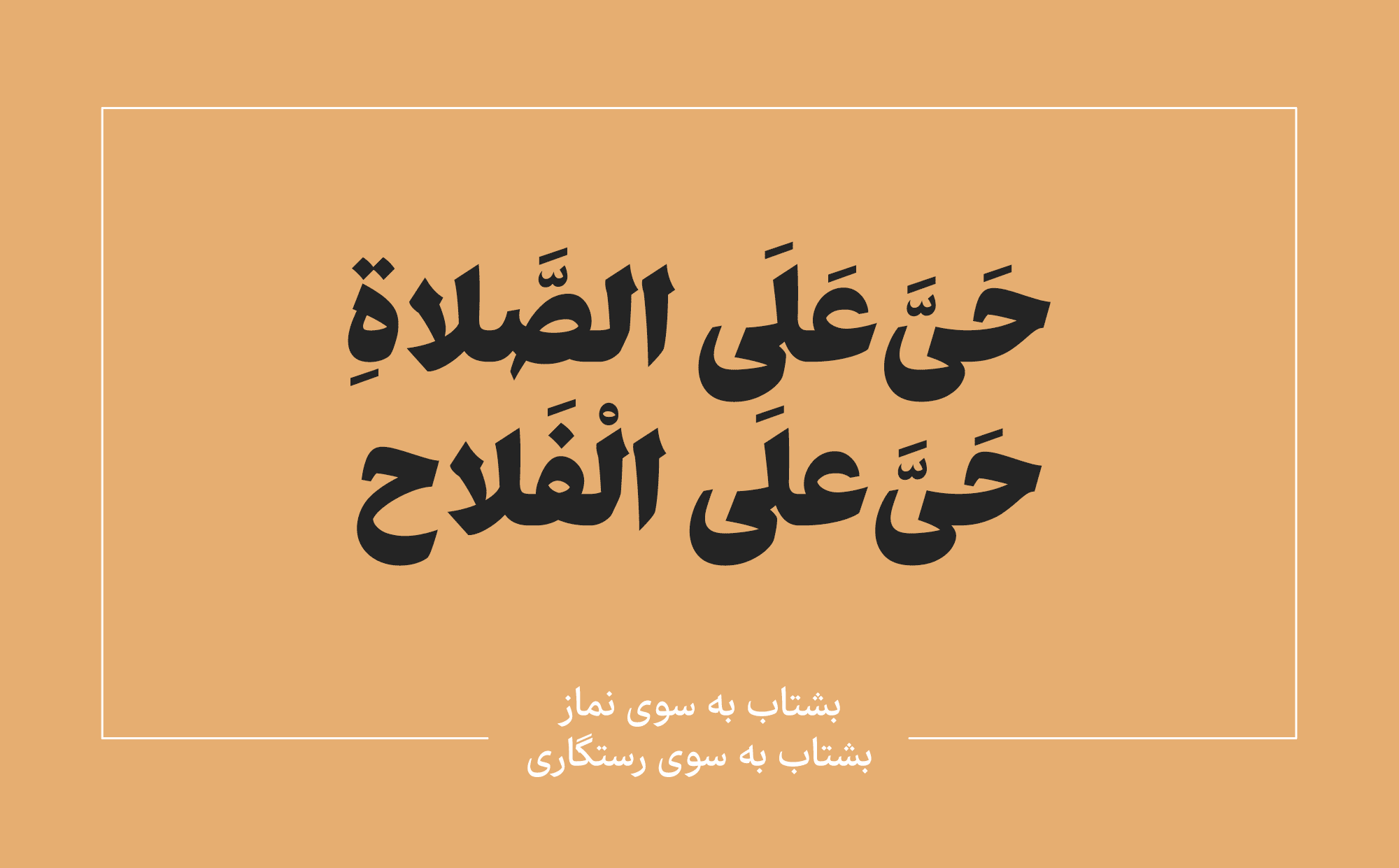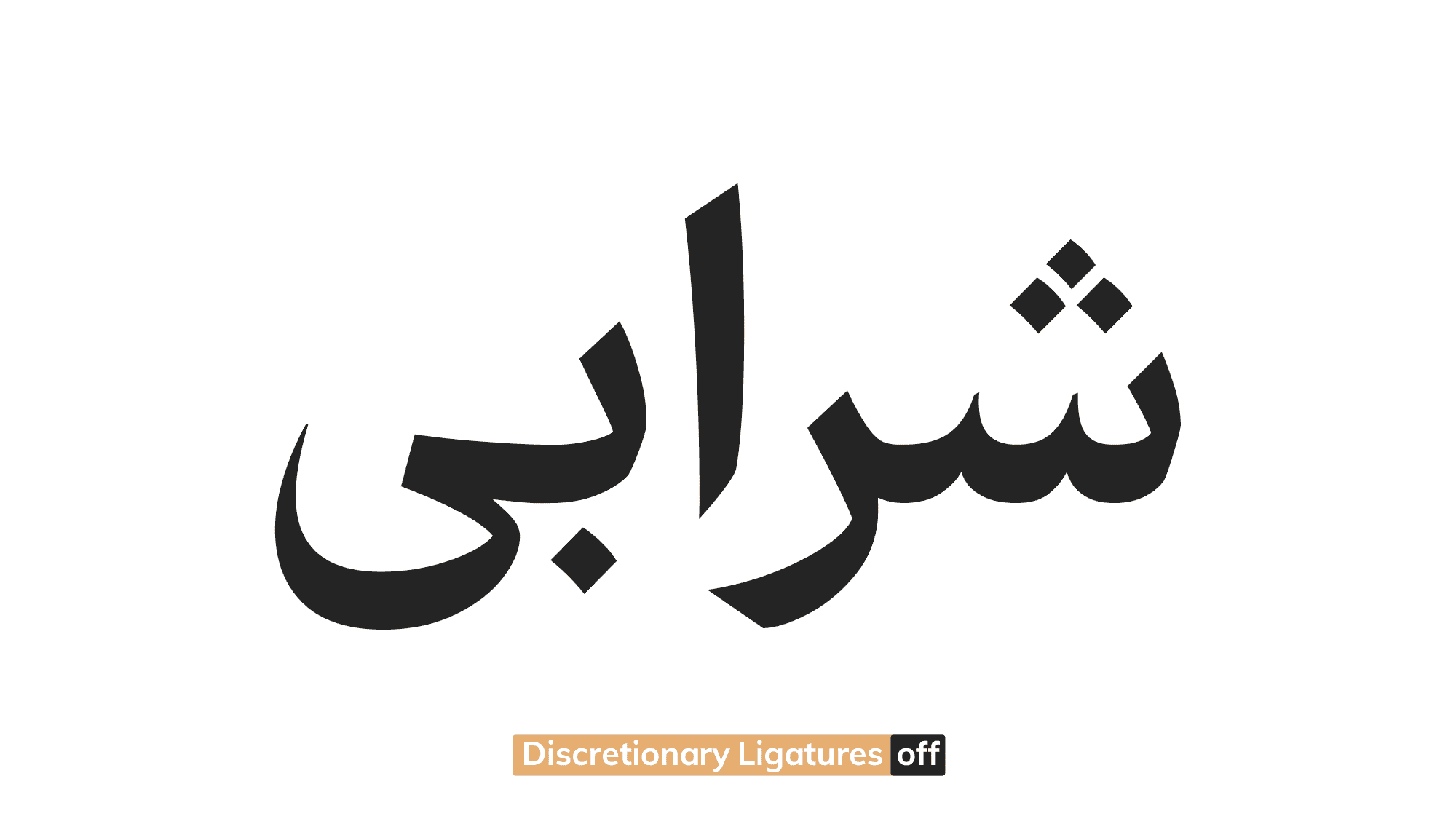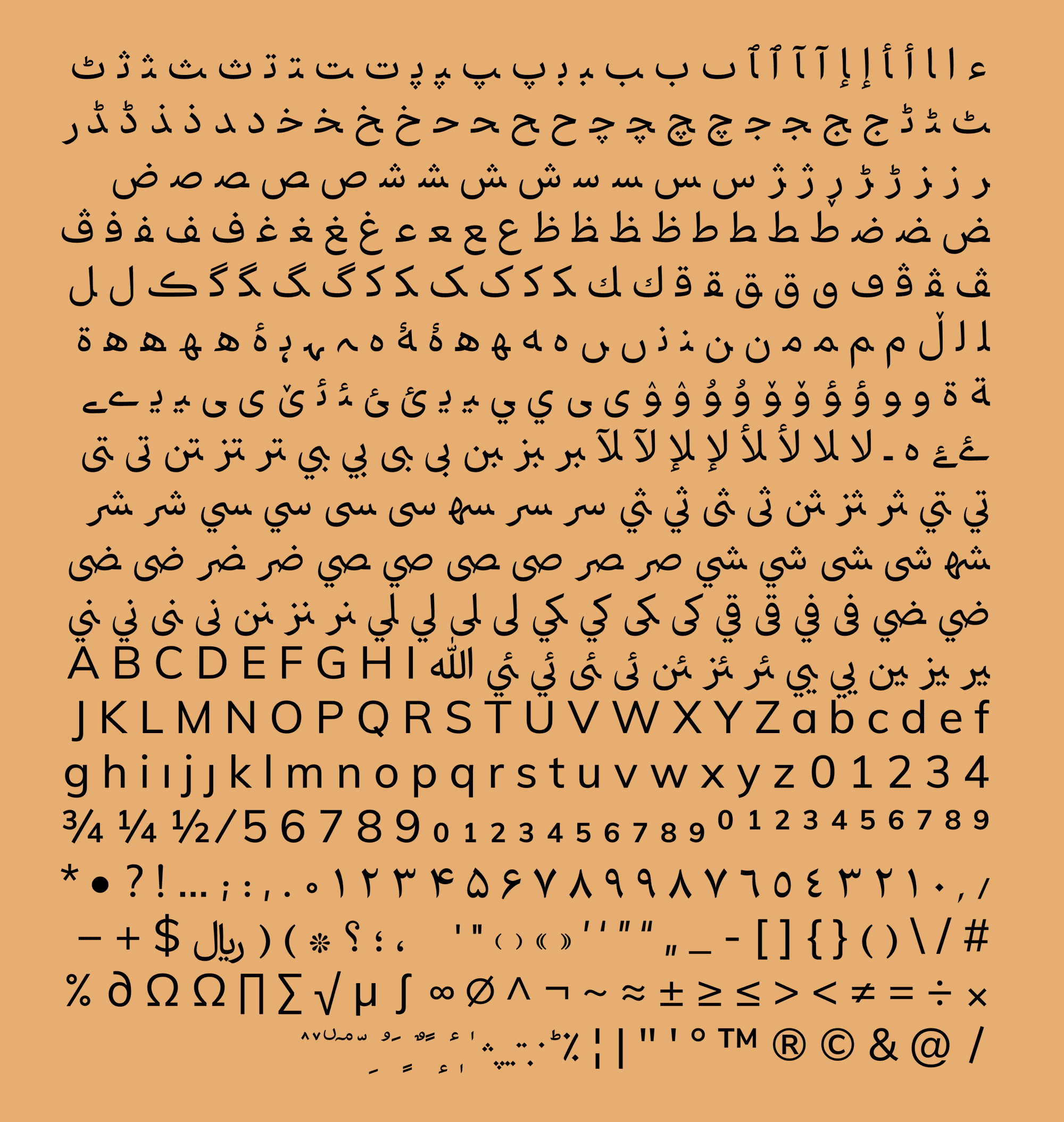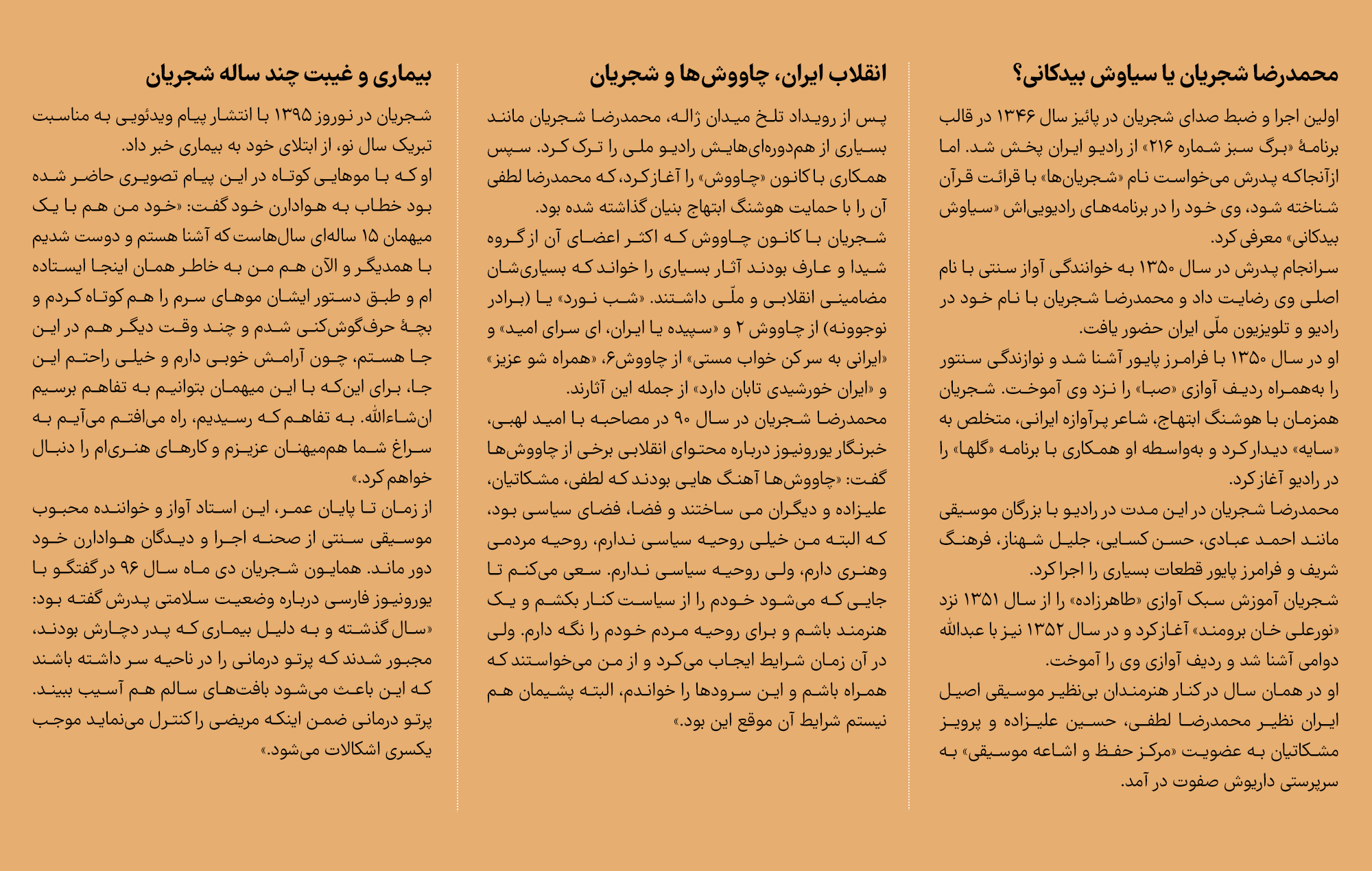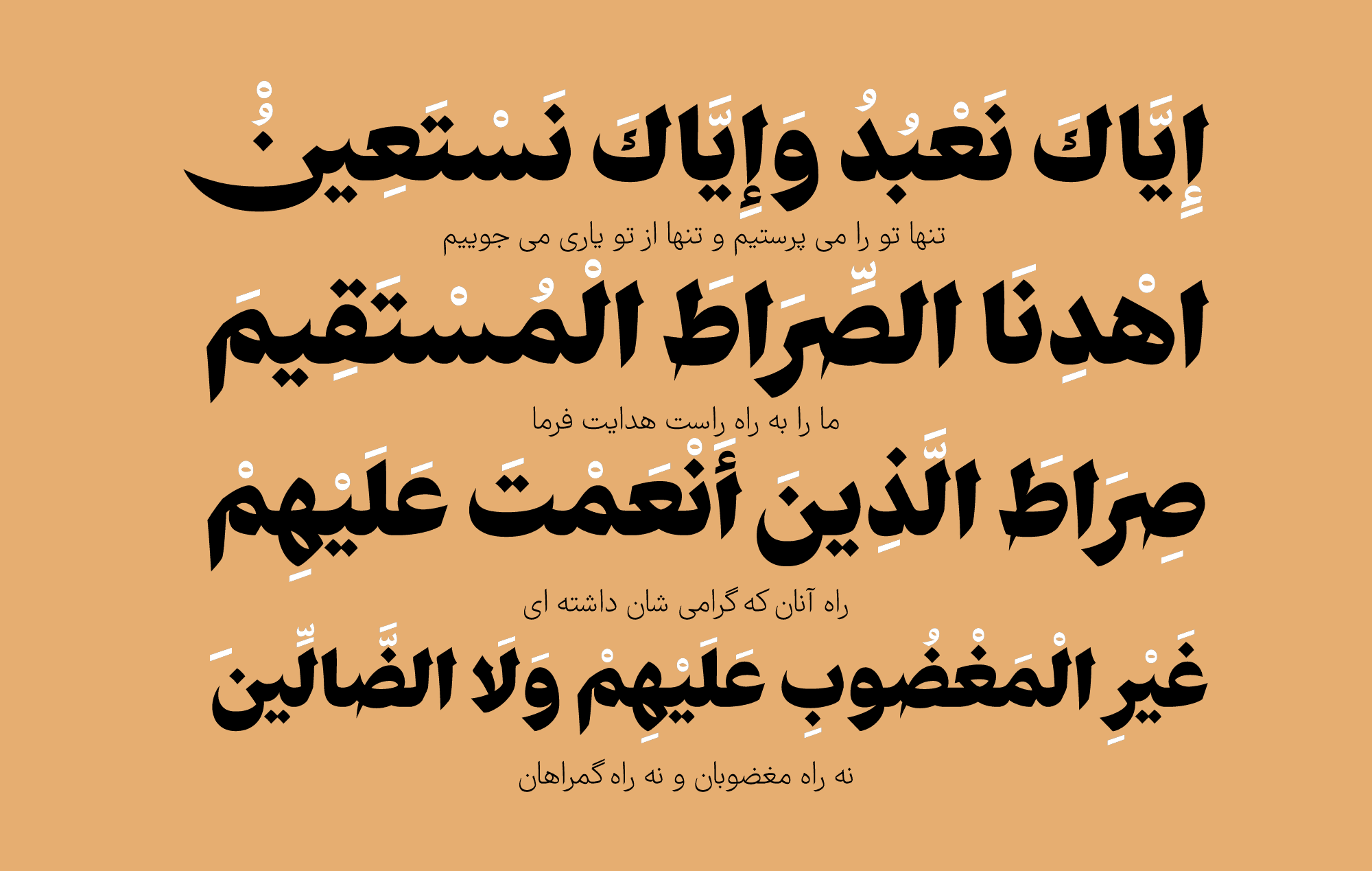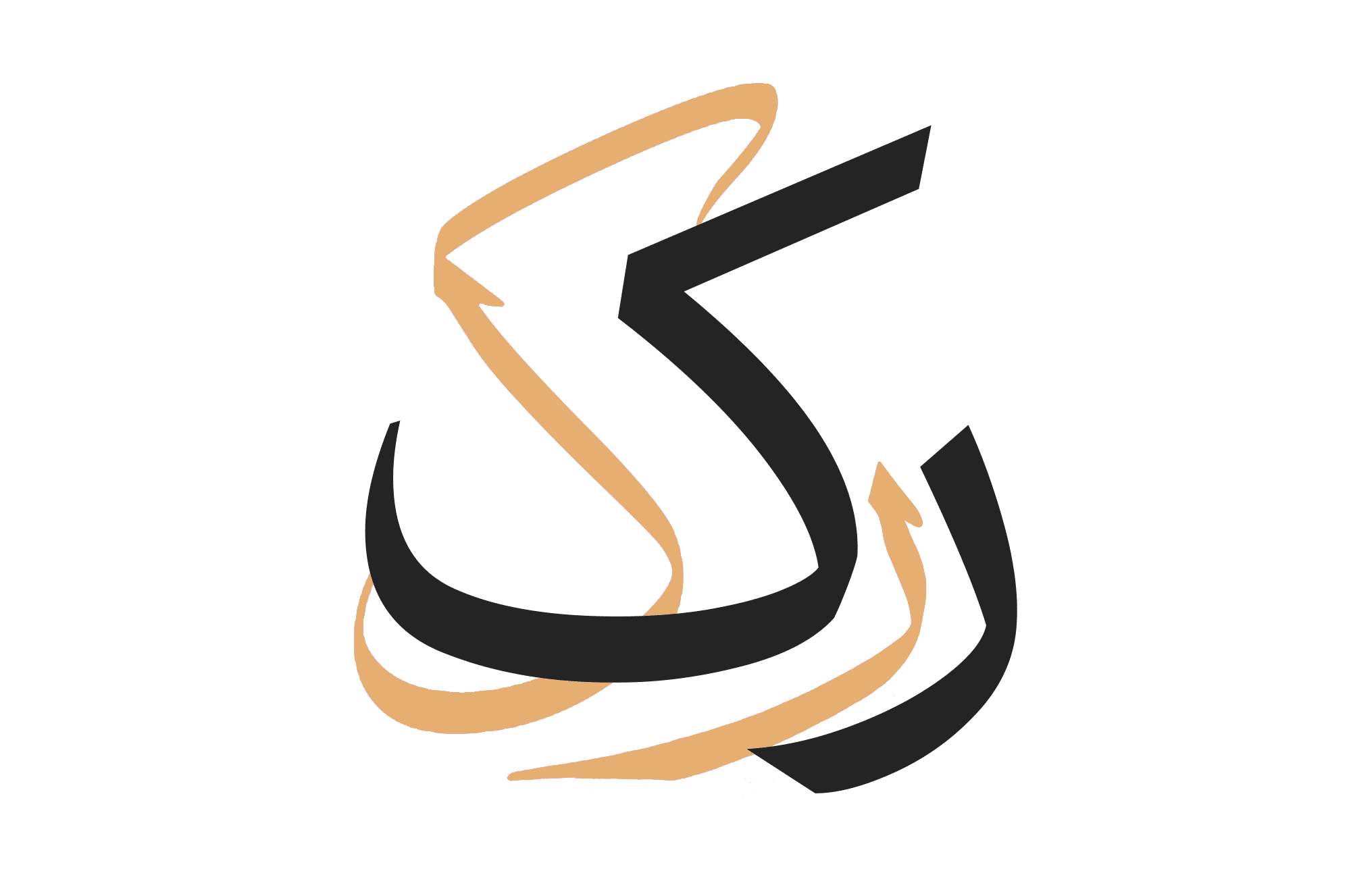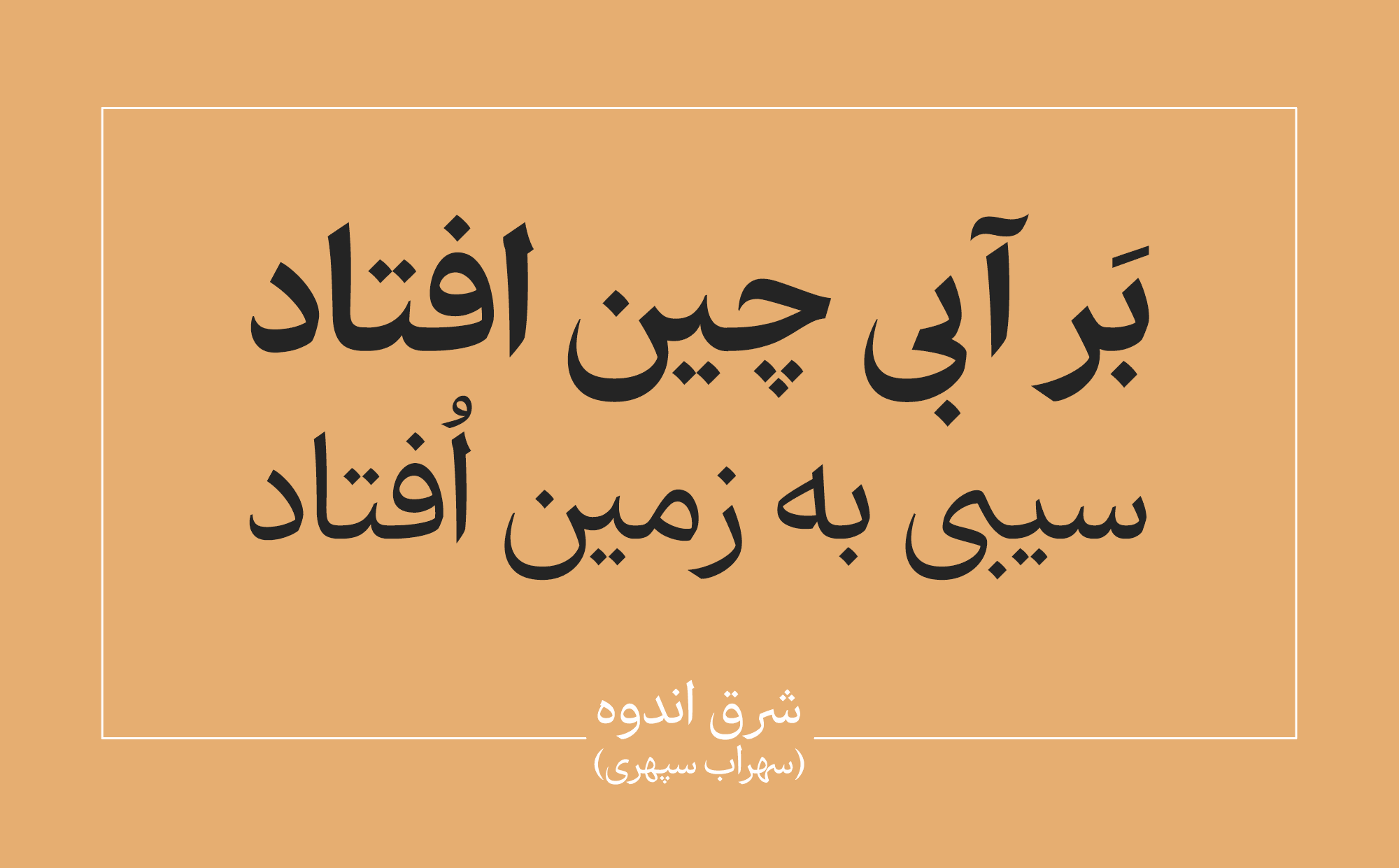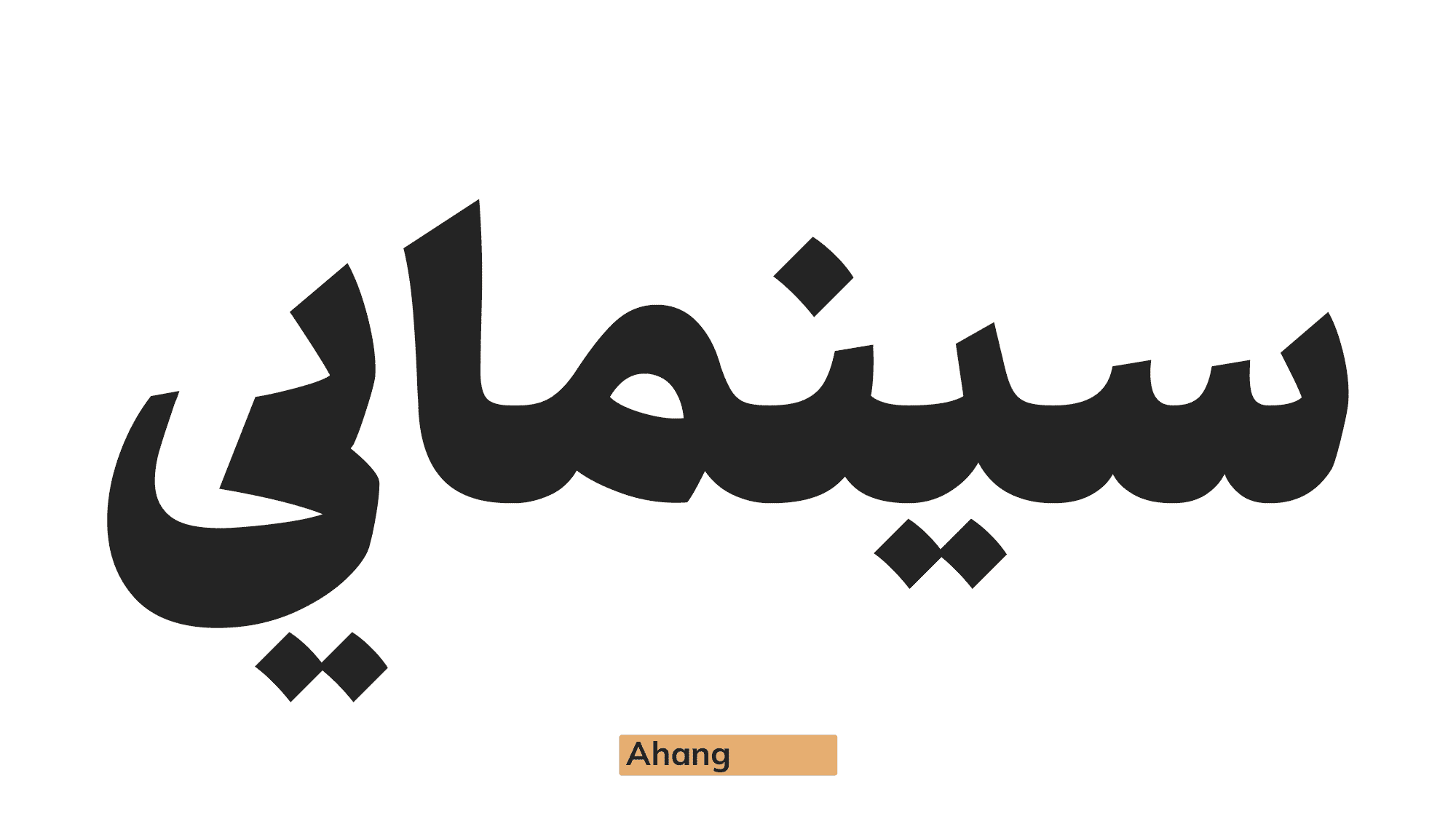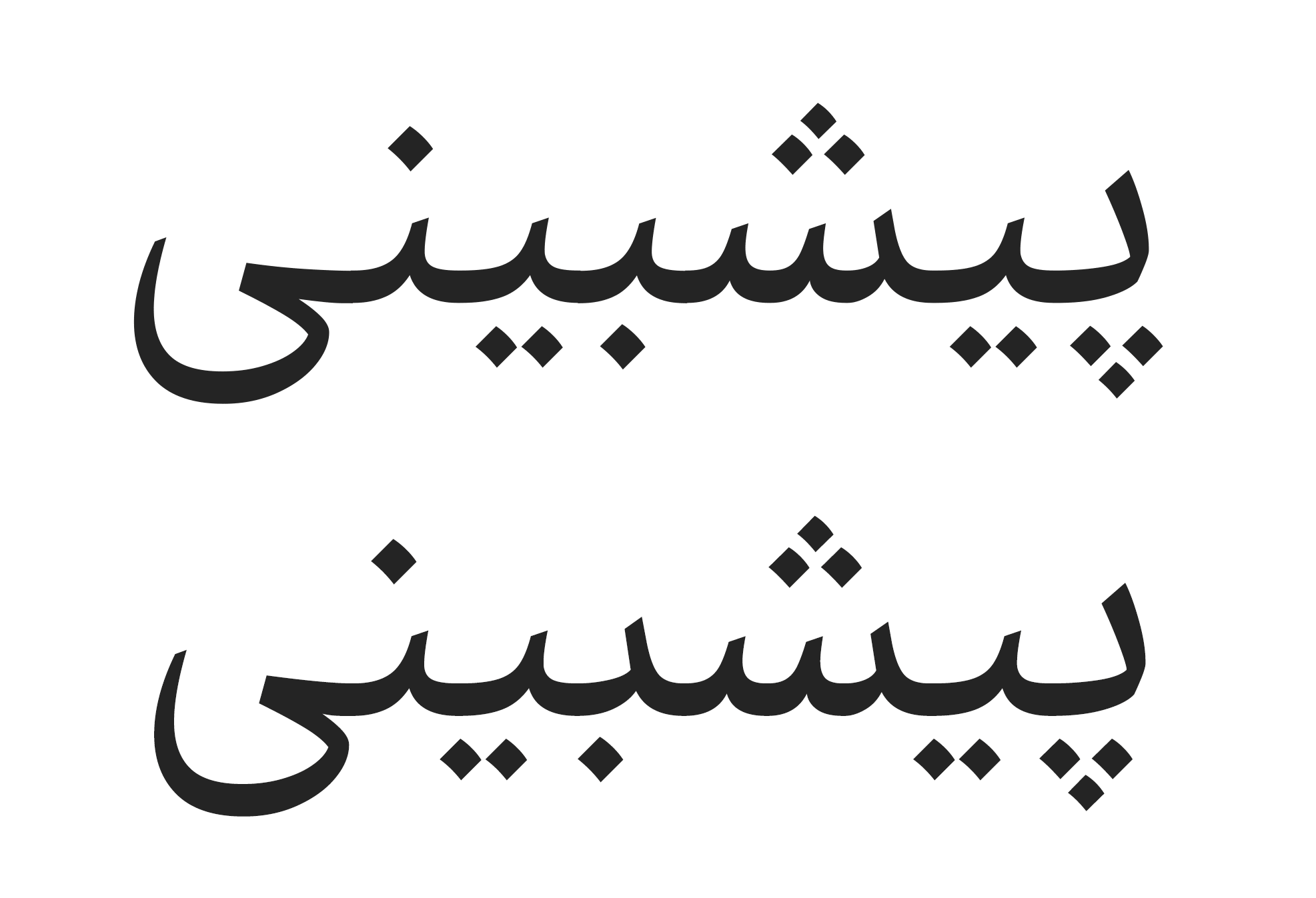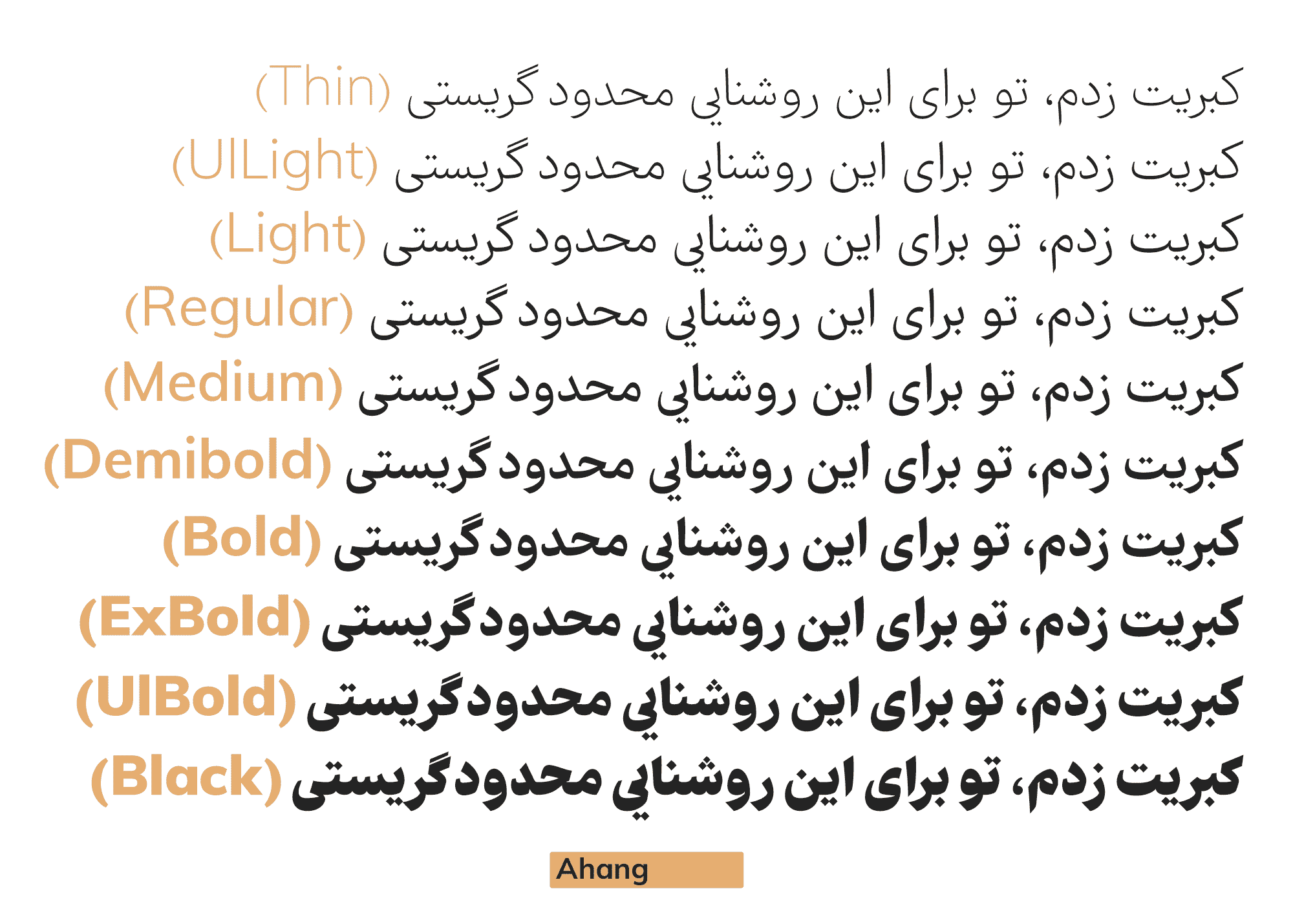
آهنگِ خطاطی
حروفی مانند ر و ک همیشه در طراحی فونتهای متن دردسرساز بودن. یکی پاشو از گلیم خودش درازتر کرده، اون یکی هم سرک کشیده به فضای حرف همسایه.
برای همینه که در طراحی فونتهای فارسی به مرور اندازه ر و ک رو کوچیک کردن.
در فونت آهنگ اما ر و ک ، پاشنه بلند و سرکش هستن! این باعث شده حس و حال خطاطی در این فونت باقی بمونه.
فونت آهنگ و آهنگِ شارپ
فونت آهنگ با دندانههای تخت، با صلابت و قدرتمند به نظر میرسد. اما در آهنگ شارپ (با تیز شدن دندانهها و انتهای حروف) با فونتی مواجه میشویم که اصالت خطاطی و ظرافت هنری را نشان میدهد.
در وزنهای پایینتر تفاوت فونت آهنگ و آهنگ شارپ بسیار کم است و بیشتر جنبه کاربردی دارد. وجود دو استایل فونت متن با کنتراست متفاوت به شما این امکان را میدهد که با توجه به نوع کاغذ و چاپ یا شرایط نمایشگر دیجیتال نسخه سیاهتر (آهنگ) یا نسخه ظریفتر (اهنگ شارپ) را انتخاب کنید.
ترکیبات اختیاری Discretionary Ligatures
در فونت آهنگ تعدادی ترکیبات وجود دارد که باعث زیبایی بیشتر فونت میشود. لازم است به صورت دستی این ترکیبات اختیاری را فعال کنید. نظر ما این است که در متن ریز این ترکیبات خوانایی را کاهش میدهند و حروف در حالت اتصال ساده و خطی راحتتر خوانده میشوند.
طرههای تزئینی
در فونت آهنگ میتوانید با فعالسازی Stylistic set طرههای تزئینی مروسوم در خوشنویسی نسخ و ثلث را به حروف ا ل لا ک ص ط اضافه کنید.
حروف جایگزین
اکثر حروفی که دوست دارید در فونت به عنوان جایگزین انتخابی استفاده کنید (مثل ﮧ ﮩ مدل نستعلیق و ے معکوس) حروف زبان اردو هستند. از آنجا که فونت آهنگ این حروف اردو را دارد امکان استفاده از آنها در کیبورد فارسی نیز برای شما فراهم شده است. حروفی مثل م و ع هم چون در خوشنویسی به شکلهای مختلف نوشته می شود به عنوان جایگزینِ حروف اصلی به فونت آهنگ افزوده شده است.
این حروف جایگزین را طبق راهنما و به راحتی در هر محیطی میتوانید تایپ کنید.
چینش دقیق نقطهها و دندانهها
حروفی مانند ب ب ت ت پ پ ث ث ن ن ی ی س س ش ش گروه پر جمعیت خط فارسی هستند که شکل کاملا مشابهی دارند. چشم تنها با تشخیص فواصل و نقطهها آنها را از هم تشخیص میدهد.
در فونت آهنگ هر دندانه با توجه به حروف قبل و بعد خود شکل و جای نقطهٔ خود را طوری تعیین میکند تا نهایت نظم و زیبایی در شکل کلمات بدست آید.
نکته: به دلیل وجود محدودیتهای حروفچینی در دستگاههای اولیه چاپ جای نقطهها مایل به راست است و این رسم در فونتهای دیجیتال نیز باقی مانده است.
در فونت آهنگ نقطهها در جای درست خود یعنی زیر حرف مربوط به آن قرار دارند.
همانطور که در سطرهای بالا توضیح دادیم در فونت آهنگ نقطهها بصورت برنامهریزی شده در محل ایدهآل قرار می گیرند بدون اینکه برای حل مشکلات برخورد، عرض حروف زیادتر شود یا فضای خالی بیش از حد پدید آید.
فونت متغیر (وریبل فونت)
وریبل فونت تکنولوژی جدیدی در ساخت فونت است که به شما این امکان را میدهد که همهی وزنها و استایلها را در قالب یک فایل فونت در اختیار داشته باشید.
به کمک فونت متغیر میتوانید کنتراست ضخامت و میزان تیز یا تخت بودن دندانهها را کنترل کنید و از ضخامتهای مابین وزنهای ۱۰ گانه نیز استفاده کنید.
Weight : این متغیر وزن (ضخامت) نوشته را تعیین میکند که حداقل آن 100 معادل وزن Thin و حداکثر آن 900 معادل وزن Black است.
Sharp : این متغیر دندانهها و انتهای کاسه حروف را تیز میکند و کنتراست ضخامت را کمی بیشتر. مقدار این تغییر را در گستره 0 تا 100 میتوانید تنظیم کنید.
در ادامه میتوانید نمونههای تایپوگرافی شده با فونت آهنگ و آهنگشارپ را ببینید: